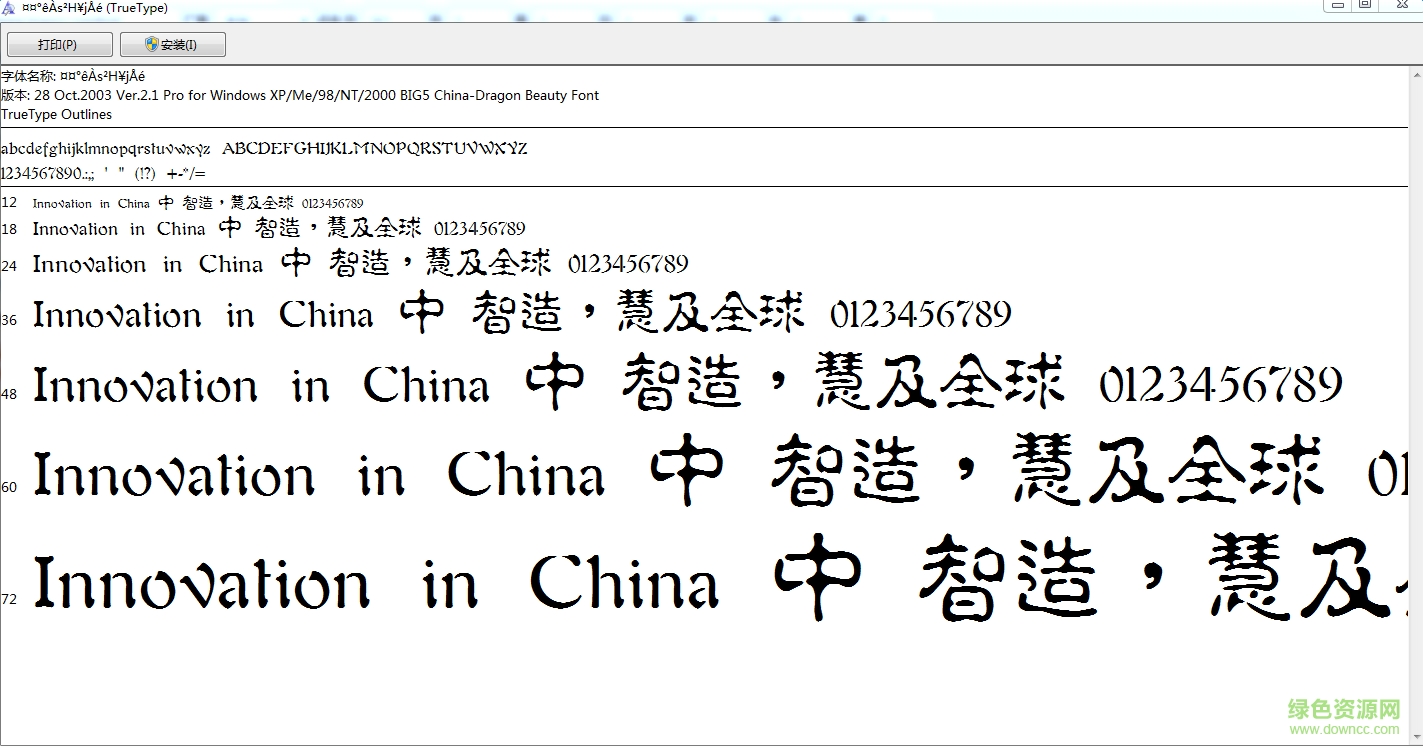
中国龙淡古体简体
中国龙淡古体是一款典雅的中文古体字体,字体流畅超逸,笔画飞动,看上去非常漂亮!喜欢的该款字体的朋友快来绿色资源网下载吧!
中国龙淡古体字体介绍
中国龙淡古体是一款用于美工设计方面的字体,整体效果非常统一,且字库完整,可以广泛应用于广告设计、海报、ppt、影视制作以及内容用字等领域,有需要的朋友可以免费下载收藏。
中国龙淡古体样貌